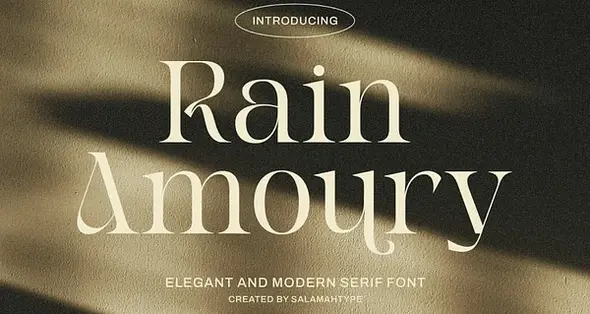
• فونت انگلیسی ژورنالی شیک
• Rain Amoury Elegant Font
فونت انگلیسی ژورنالی شیک
• circle سبک قلم: Serif
• circle حروف کوچک
• circle حروف بزرگ
• circle لیگچر
فونت Rain Amoury یک تایپ‌فیس سریف صیقلی و استایلیش است که برای طراحی لوگو، مراسم عروسی، برندهای زیبایی، دنیای مد و موارد دیگر انتخابی ایده‌آل محسوب می‌شود. این فونت با منحنی‌های نرم، جزئیات فانتزی و یک نسخه کج (Oblique)، ظاهری آراسته و سطح بالا به هر پروژه‌ای می‌بخشد.
Rain Amoury is a sleek, stylish serif font that’s perfect for logos, weddings, beauty brands, fashion, and more. With smooth curves, fancy details, and an oblique version, it makes any project look polished and high-end.
Features:
- Alternates & Ligatures
- Oblique Version